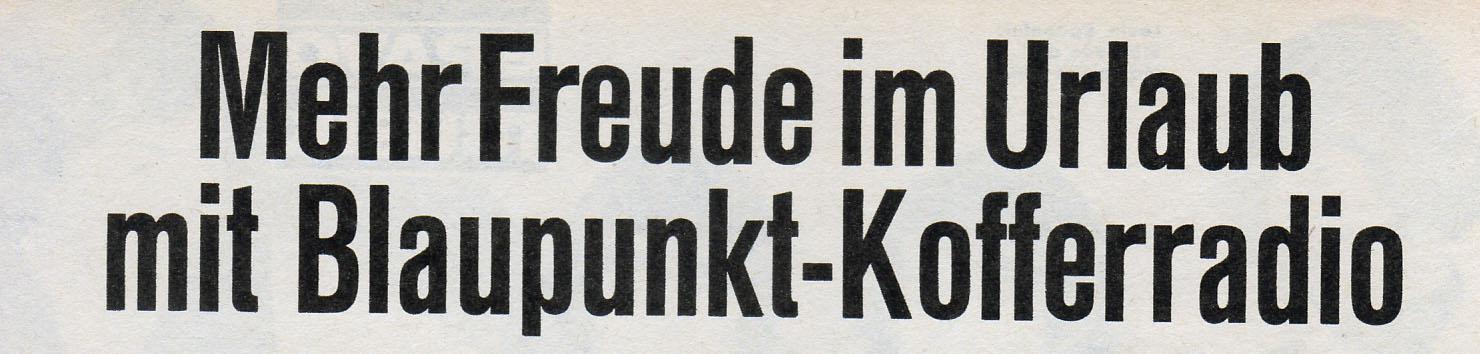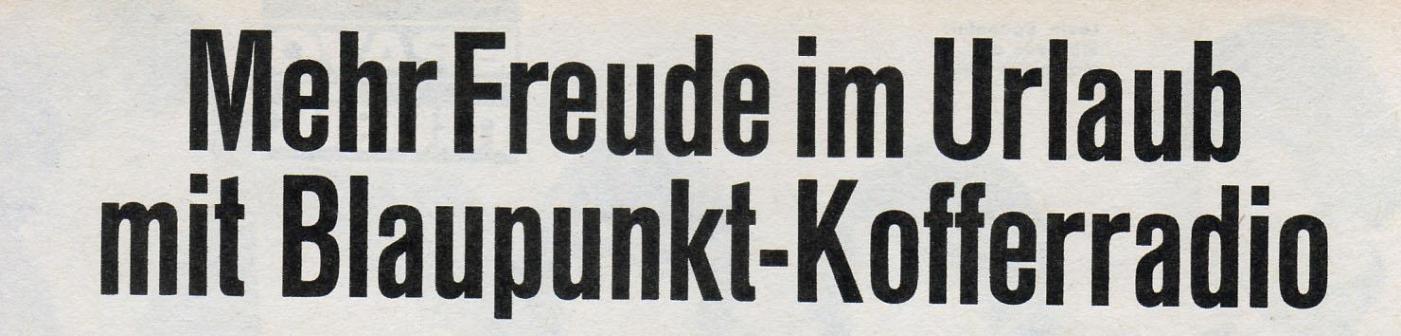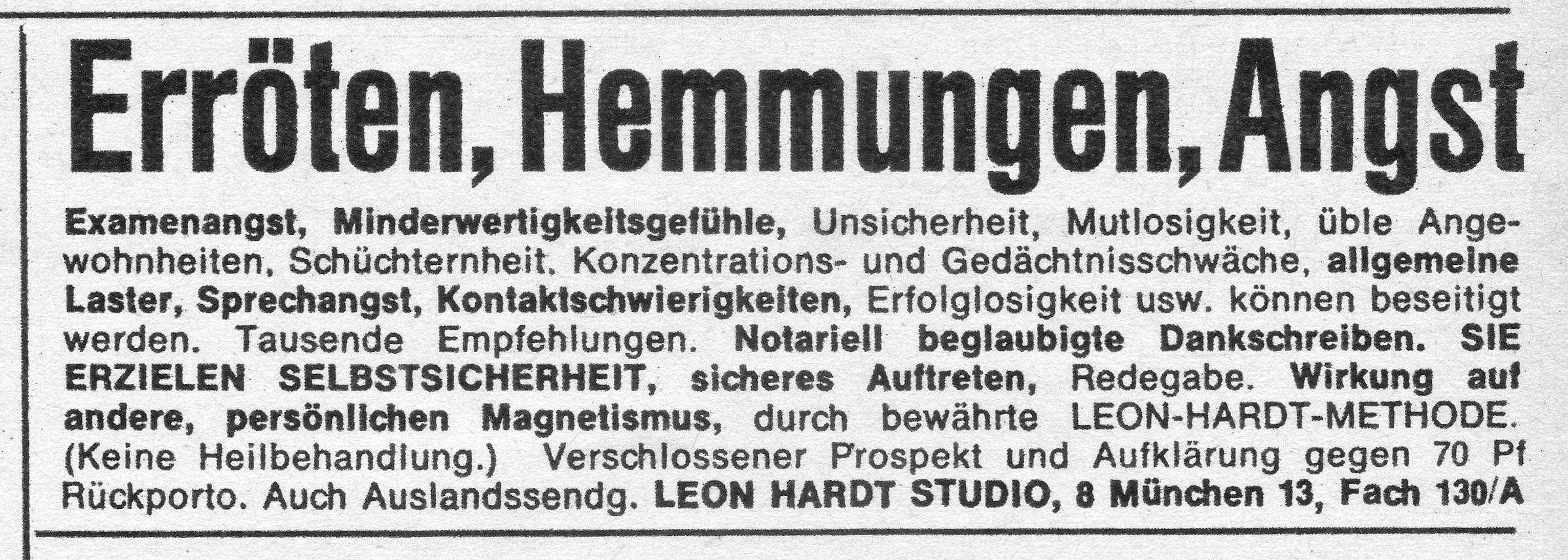
Schmalhalbfette Grotesk aus den 60er Jahren
in einem BRAVO-Heft von 1966 wird des Öfteren eine schmalhalbfette Grotesk
verwendet, wie sie in den 60er und 70er Jahren sehr oft und gern eingesetzt wurde.
Sie ist der Helvetica am ähnlichsten, doch das abgeschrägte "t" bringt mich zum Zweifeln.
Es ist die halbfette Commercial.
Wurde sie (mit dem schrägen "t")
inzwischen digitalisiert?
Existiert die halbfette Commercial-Grotesk unter einem anderen Namen als Digitalsatz?
Ich habe mal einen Wandkalender mit einem Werbetext in dieser schmalen Groteske gesehen.